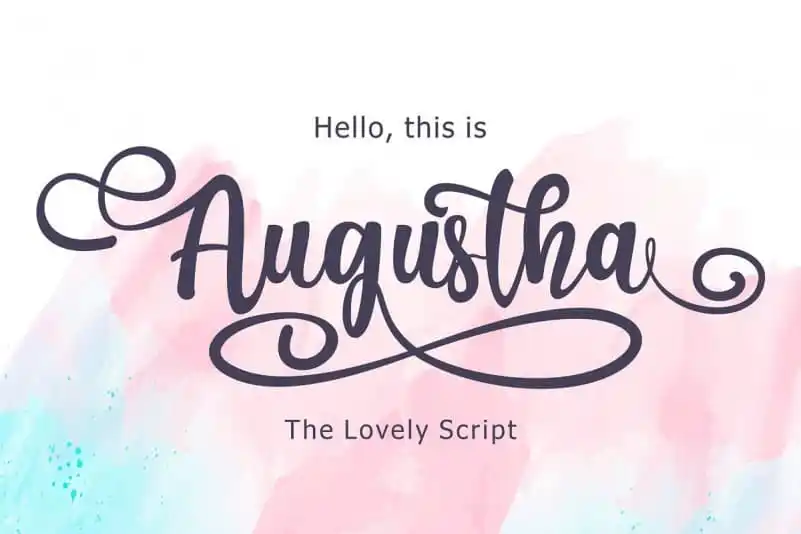
Augustha Script Font – Download Grátis
Olá fonte entusiasta! Estou aqui para apresentar à você a font Augustha. É uma nova fonte feita a mão com estilo elegante do tipo caligrafia. Pode experimentar sua primeira impressão digitando o nome que deseja, abaixo. Foi criada e compartilhada pela figuree studio. Essa é uma fonte de escrita graciosa. Ela possui um estilo marcante e elegante e é perfeita para criar designs originais. E é ótima para criação de cartões de aniversário, materiais de marca, cards de negócios, citações, panfletos, além de diversos outros usos como blog, estaçãoamento, marketing, revistas e mais! Essa fonte também faz um ótimo trabalho em postais de casamento. Ou você pode criar designs únicos e originais do seu logotipo, blog, estaçãoamento, marketing, revistas e muito mais :).